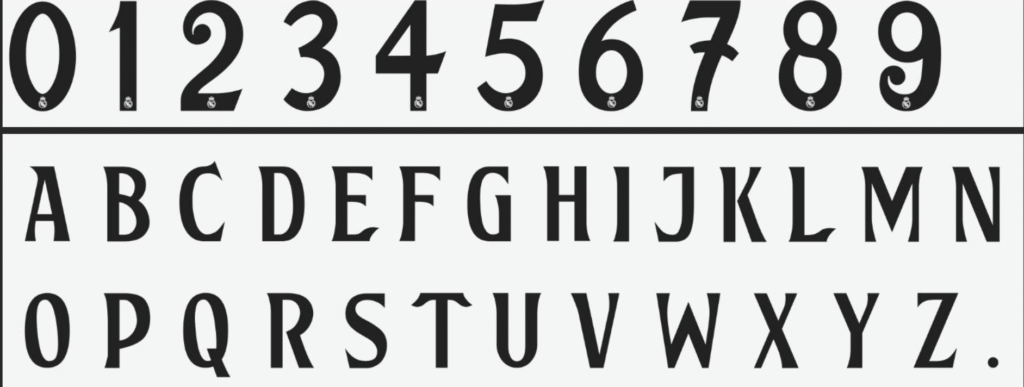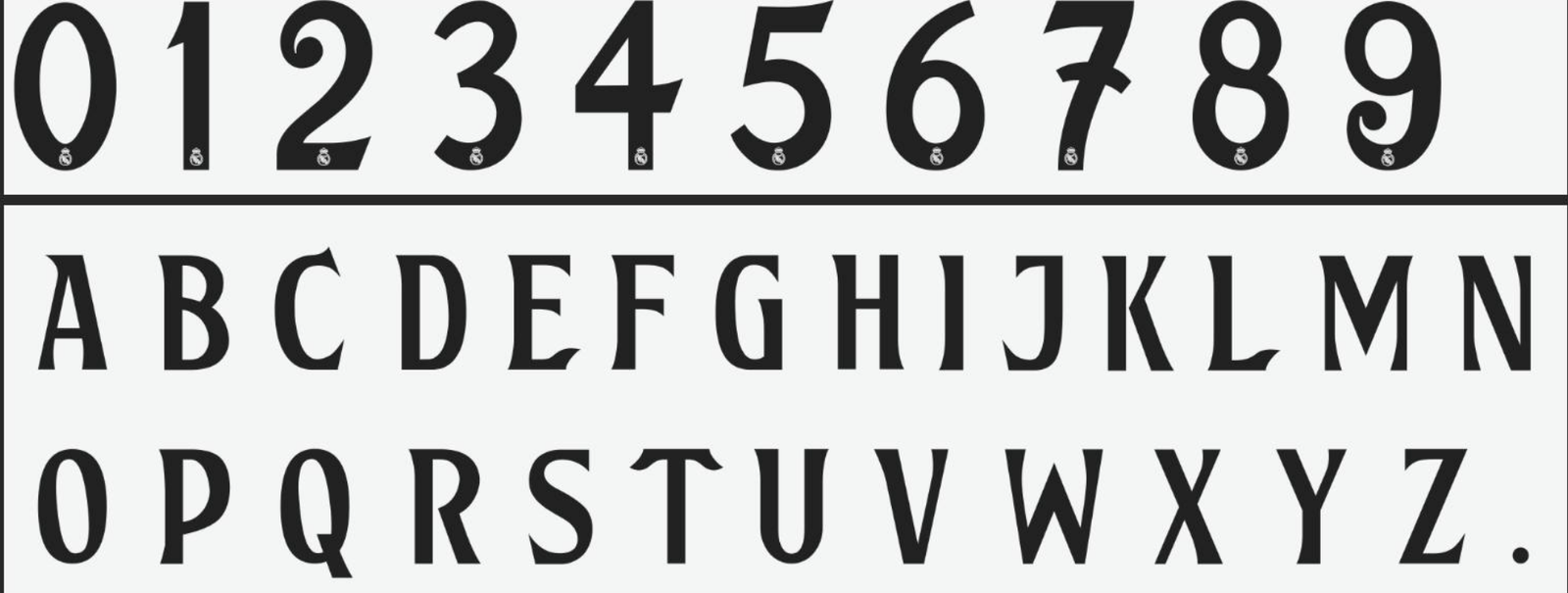
A temporada 2024/2025 marca uma nova “Era Galáctica” no Santiago Bernabéu. Com um elenco estelar e a tradicional camisa branca pesando em campo, o Real Madrid entra em cena vestindo seu novo manto produzido pela Adidas.
Para designers, personalizadores e fãs que desejam replicar o uniforme usado na Champions League e nas Copas, trazemos o arquivo exato da tipografia. Esta é a fonte personalizada (diferente da fonte padrão da La Liga), usada pelos Merengues nas noites europeias onde a mística do clube realmente brilha.
Estilo Visual e Aplicação
A tipografia desenvolvida pela Adidas para o Real Madrid nesta temporada reflete a elegância e a sobriedade do clube. Inspirada na herança cultural de Madri e no padrão houndstooth (pé-de-galinha) presente no tecido da camisa, a fonte apresenta traços modernos com cortes geométricos distintos.
Ela foge do minimalismo excessivo, trazendo uma presença sólida nas costas do uniforme. É a escolha perfeita para estampar nomes de craques como Vinícius Jr., Bellingham e Mbappé, garantindo que suas réplicas ou mockups tenham o visual autêntico de “Match Worn” (usado em jogo).
Dica de Especialista: Esta fonte deve ser utilizada para simular os uniformes de competições europeias (Champions League) e Copas domésticas. Para jogos do Campeonato Espanhol, a La Liga exige uma tipografia única e padronizada.